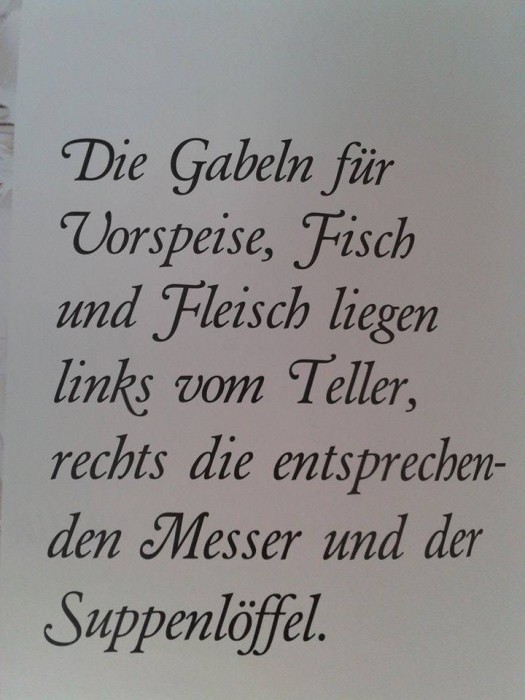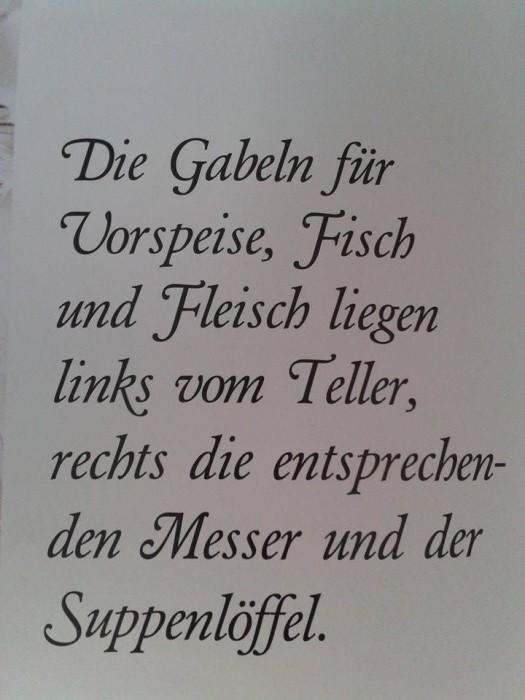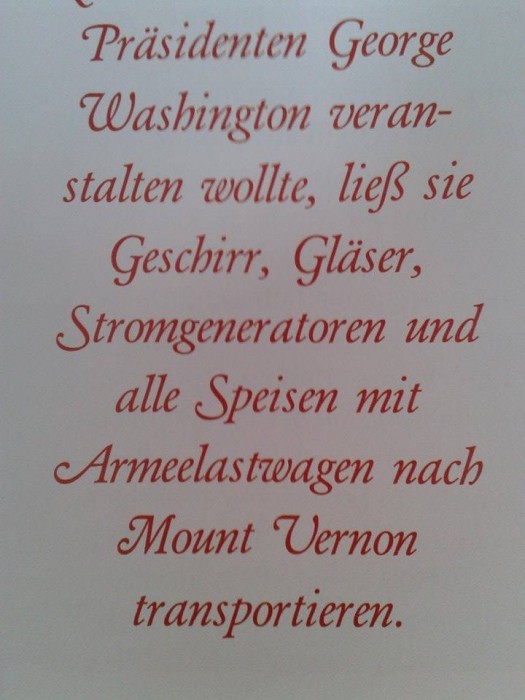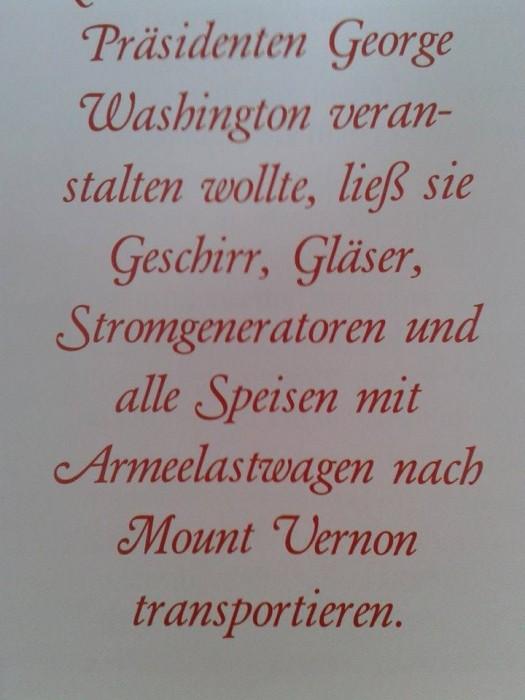
Ich bin auf der Suche nach der angehängten Schrift.
Über whatthefont finde ich sie leider nicht, ich hab so ein Gefühl, die Großbuchstaben stammen aus einem Stylistic Set...